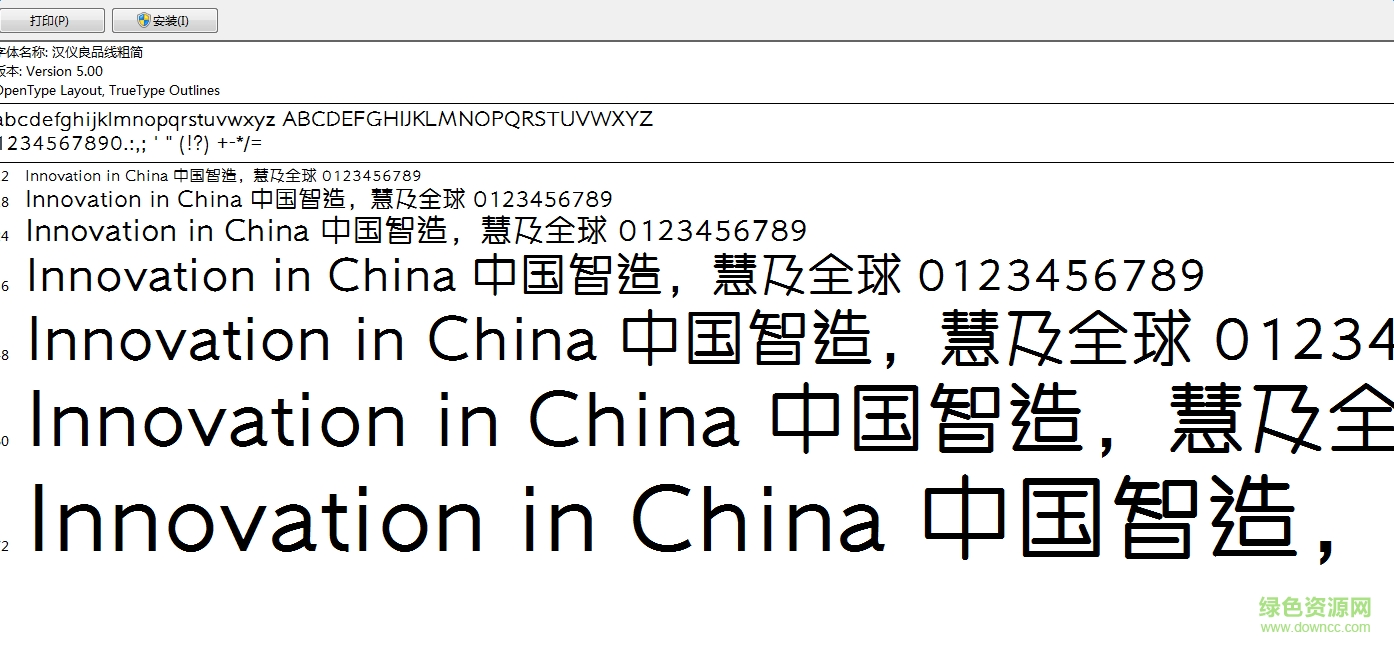
這款漢儀良品線(xiàn)粗簡(jiǎn)字體清新規(guī)整,充滿(mǎn)簡(jiǎn)約的設(shè)計(jì)感,整套字具有現(xiàn)代感。適合畫(huà)冊(cè)標(biāo)題、海報(bào)設(shè)計(jì)、廣告宣傳等場(chǎng)合使用!喜歡的朋友歡迎來(lái)綠色資源網(wǎng)下載哦!